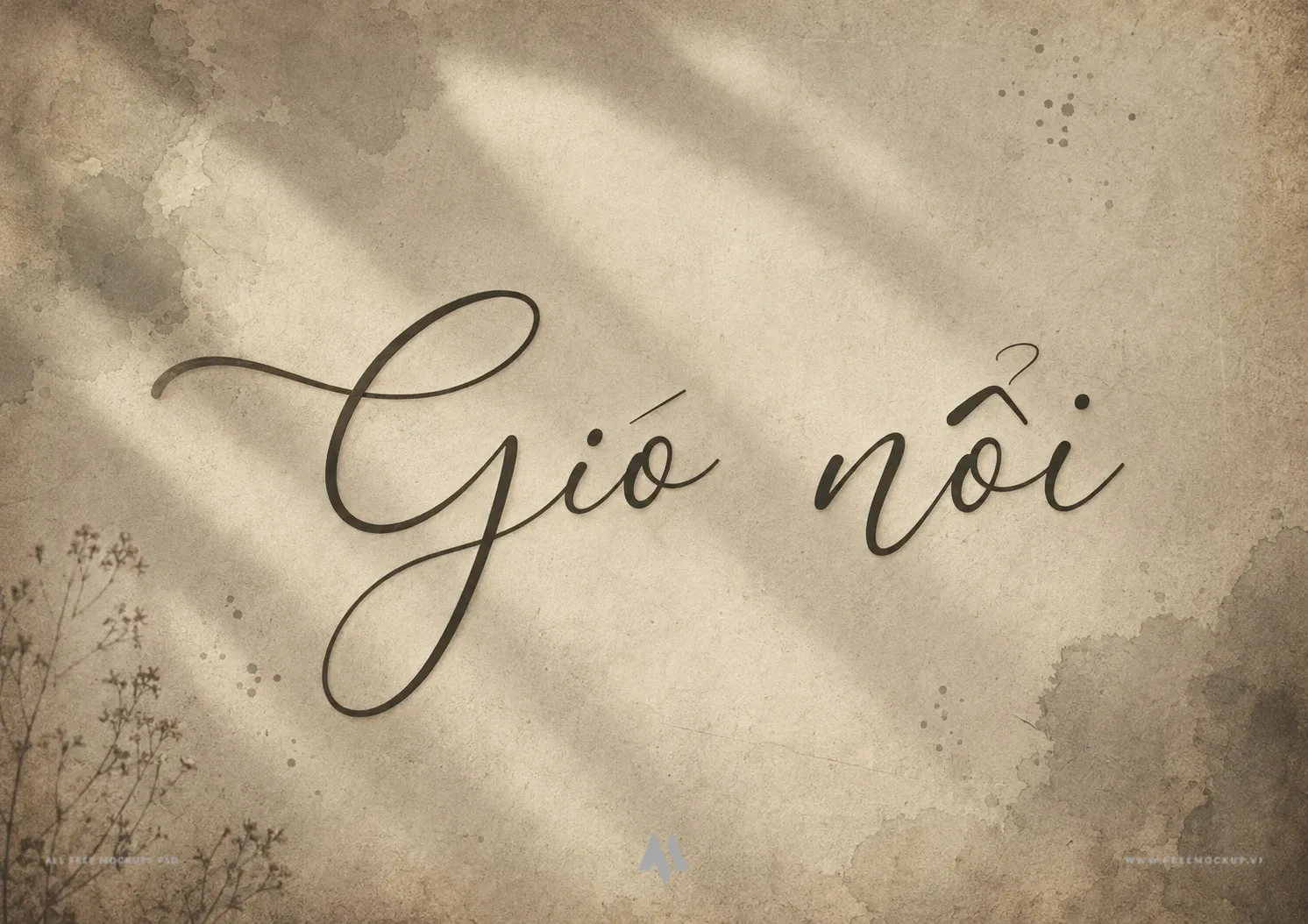
FC Daytonica Việt Hóa là bộ font chữ viết tay (Script Font) cao cấp được thiết kế bởi Timur Type và phát hành đầu năm 2025. Nổi bật với những đường nét thanh thoát, uyển chuyển và tự nhiên, bộ font mang đến cảm giác ấm áp, gần gũi và đầy chất thơ, là giải pháp hoàn hảo cho các ấn phẩm thiết kế đòi hỏi tính thẩm mỹ cao và sự tinh tế.
Đặc điểm nổi bật
- Nét bút viết tay bay bổng: Từng ký tự sở hữu độ lượn mềm mại, kết hợp cùng hệ thống ligatures (nét nối) độc đáo tạo nên dòng chảy thị giác liền mạch và tự nhiên như nét bút thật.
- Chuẩn hóa tiếng Việt & Đa ngôn ngữ: Phiên bản được đội ngũ Font Chuẩn Việt hóa tỉ mỉ, hỗ trợ trọn bộ ký tự có dấu tiếng Việt cùng hơn 64 ngôn ngữ quốc tế (Anh, Pháp, Đức, Tây Ban Nha, Ý, Bồ Đào Nha…).
Ứng dụng đa dạng trong thiết kế
- Ấn phẩm lễ hội & Sự kiện: Thiệp mừng Giáng sinh, banner Tết, thiệp chúc mừng Ngày Nhà giáo Việt Nam 20/11, thiệp cưới sang trọng và thư mời tiệc thân mật.
- Nhận diện thương hiệu & Bao bì: Thiết kế logo, typography cho các lĩnh vực thẩm mỹ viện, spa, mỹ phẩm, thời trang nữ, quán cafe và ngành ẩm thực.
- Xuất bản & Quà tặng: Bìa sách nghệ thuật, nhãn mác sản phẩm handmade, hộp quà tặng và menu nhà hàng.
- Truyền thông số: Poster quảng bá sự kiện, visual marketing và hình ảnh truyền cảm hứng trên mạng xã hội.